アデニウム
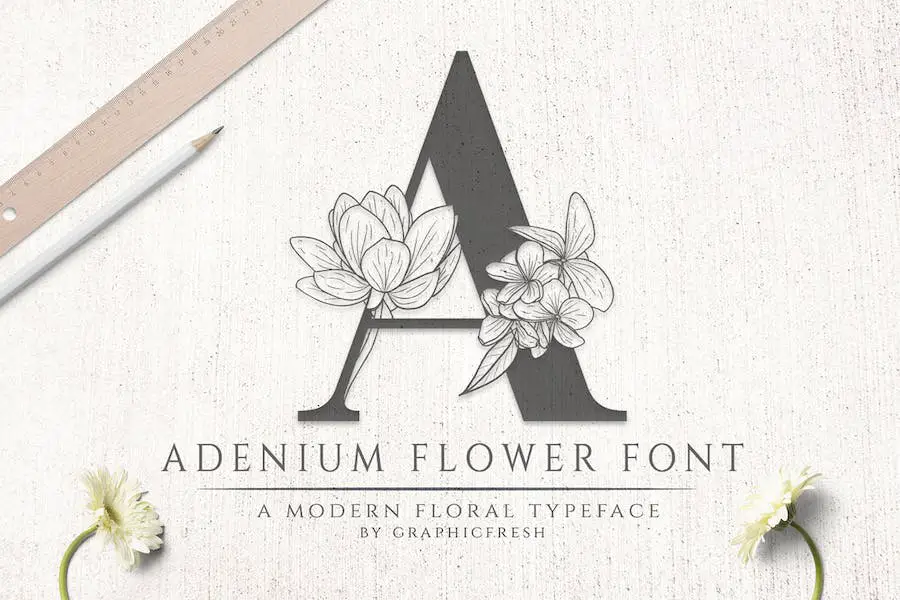
エレガントなフランジパニの花からインスピレーションを得た Adenium フォントは、プロジェクトに美しさをもたらします。 そのセリフ スタイルは、これらの見事な花の本質を完璧に捉えています。
ジャングルをテーマにした結婚式、海とクルーズスタイルのイベント、またはレストラン、ホテル、ビーチ リゾートのロゴを作成する場合でも、このフォントは理想的です。
Adenium を使用すると、ユニークなブランド アイデンティティ、スタイリッシュで優雅なロゴタイプ、または絶妙な結婚式の招待状をわずか数分で作成できます。
このフォントには各文字の 2 つのバージョンが用意されており、デザインに多用途性と多様性を加えます。 大文字と小文字のバージョンでは、創造性を発揮するための異なるオプションが提供されます。
アロア
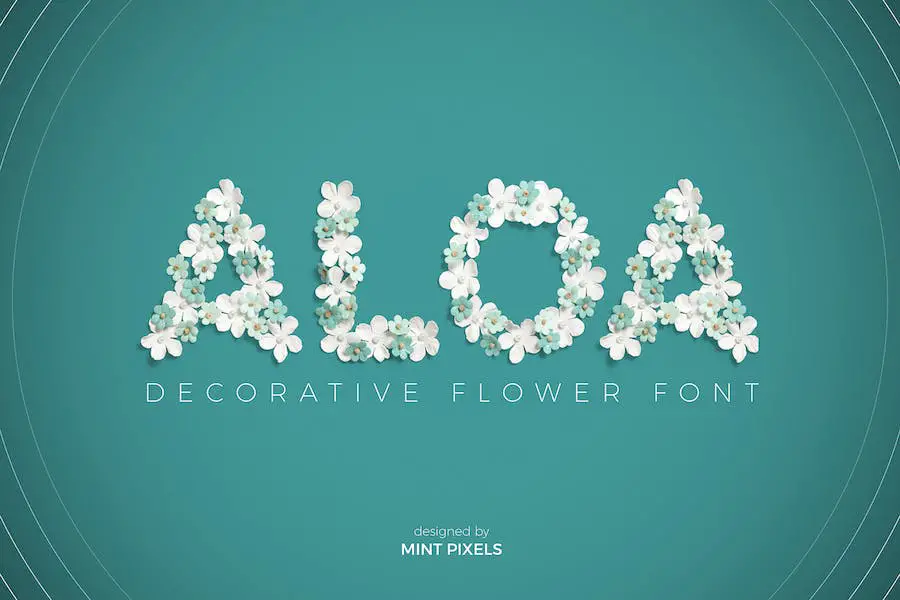
Aloa を使用すると、すべての文字、数字、句読点が得られるため、さまざまなデザイン プロジェクトに多用途なフォントになります。 結婚式の招待状、製品デザイン、イラスト、装飾品、工芸品などを作成する場合、このフォントは完璧な選択肢です。
ヴィグネリャ
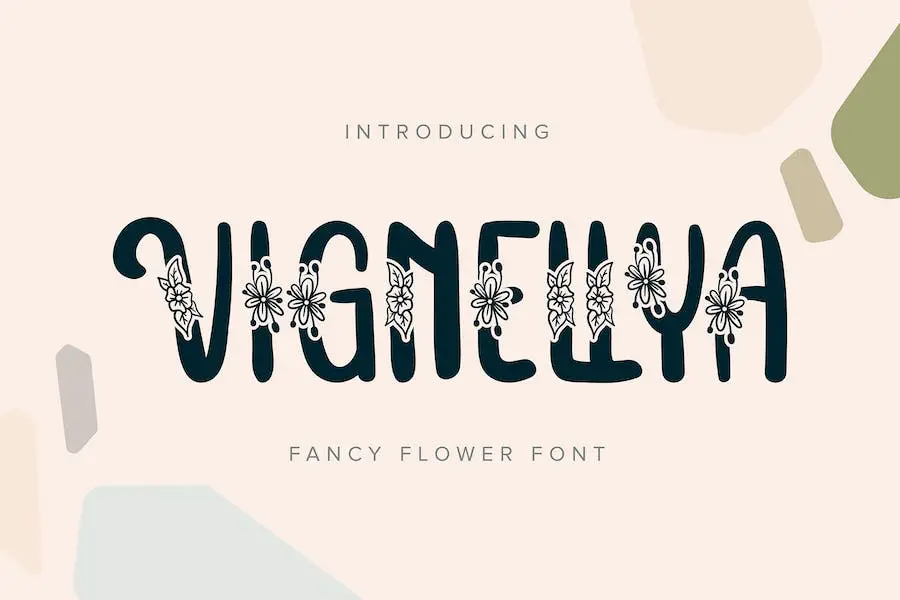
Vignellya は、美しいカリグラフィー スタイルの派手な花のフォントです。 素晴らしいグリーティング カード、ブランド資料、名刺、引用符、ポスターの作成など、プロジェクトを強化するのに最適です。
フォントには大量の代替文字が含まれており、文体セット、文体代替文字、コンテキスト代替文字、SWASH、合字などのさまざまなオープン タイプ機能に分かれています。
花の手描き
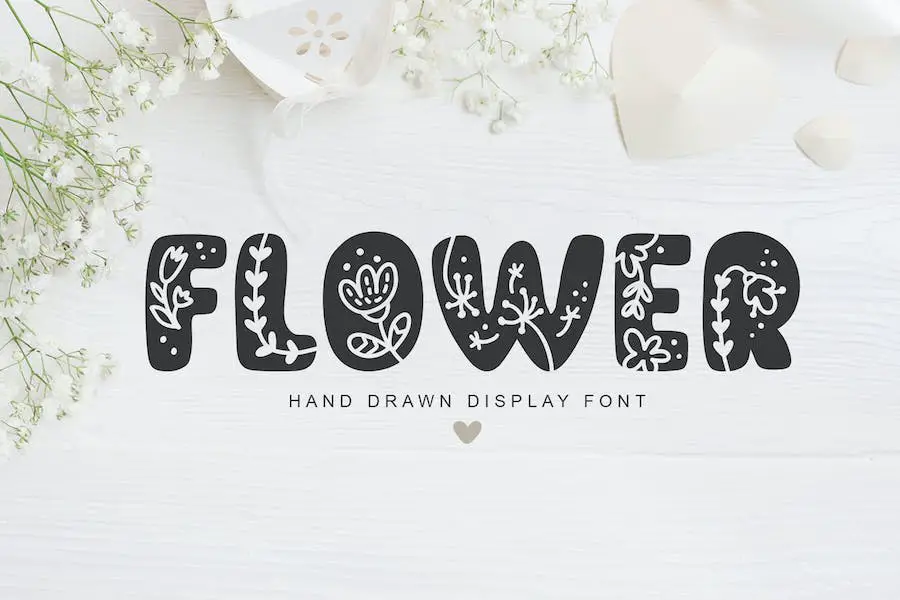
Flower Hand Drawn は、プロジェクトにスカンジナビアの魅力をもたらす楽しいバレンタイン フォントです。 手描きのスタイルと複雑なディテールを備えたこのフォントは、デザインにロマンチックで奇抜なタッチを加えるのに最適です。
このフォントにはさまざまなユニークな文字が含まれており、すべてが華やかなモノラインのハート、春の花、渦巻きで飾られています。 これらの楽しいデザイン要素により、Fflower Hand Drawn は結婚式やバレンタインデーのグリーティング カード、ロゴ、招待状などの作成に最適です。
ひまわり
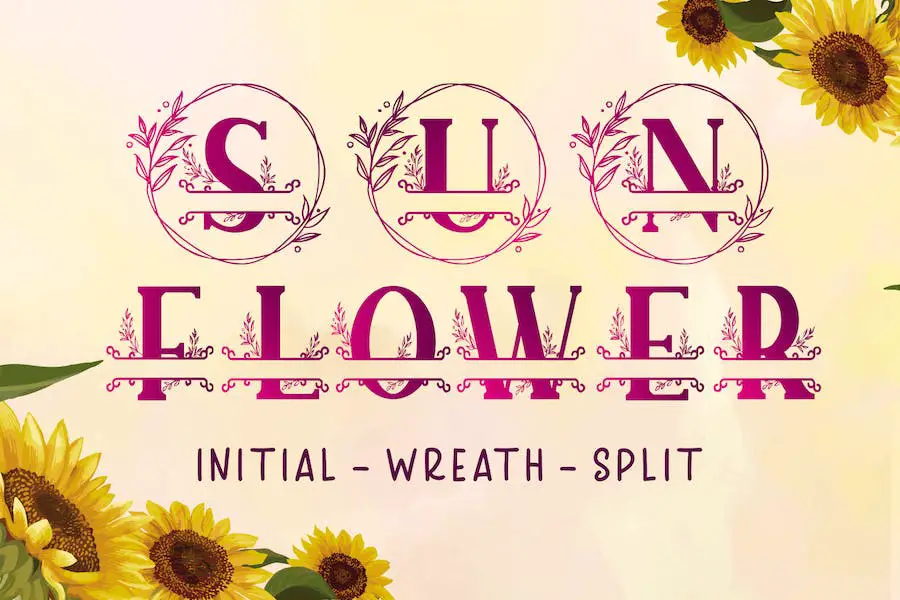
Sunflower は、あらゆるクラフト プロジェクトに個性的なタッチを加えるのに最適なフォントです。 PUA でエンコードされているため、すべてのグリフと合字に簡単にアクセスできます。 ブランド化プロジェクトに取り組んでいる場合でも、家の装飾に取り組んでいる場合でも、Sunflower は理想的なフォントです。
特に結婚式の招待状やブログのデザインに最適です。 ロゴや美しいフレームの作成にも使用できます。 Sunflower は多用途なので、ビジネス目的、ブックカバー、文具、マーケティング資料、雑誌などに使用できます。
キュートでスイートなモノグラム スタイルは、一緒に使用しても、別々に使用しても、あなたの工芸品にシックで陽気なタッチをもたらします。 ひまわりと恋に落ちて、素晴らしいデザインを作りましょう!
カンドレーヴァ
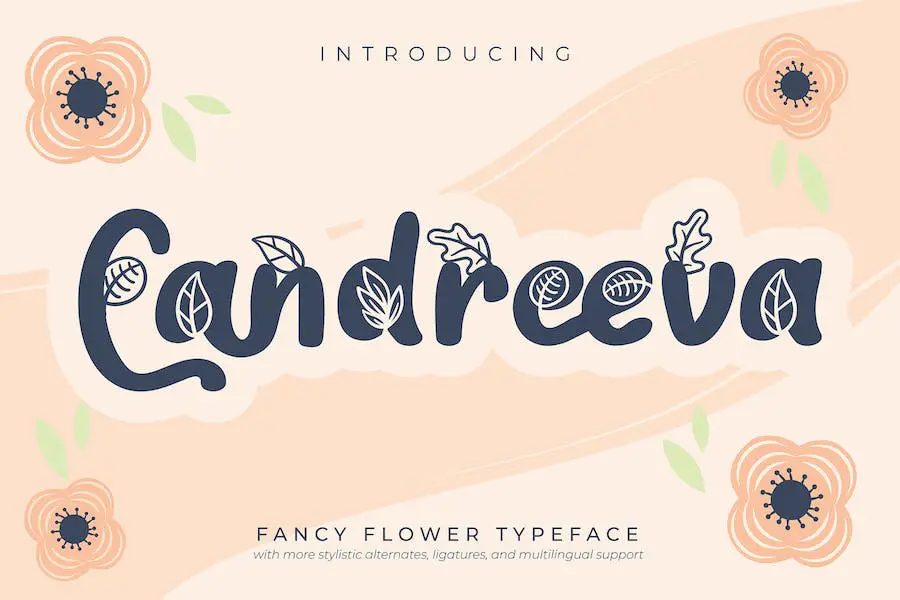
Candreeva は、あらゆるデザイン プロジェクトに優雅さを加える、派手な花の書体フォントです。 カリグラフィー スタイルと美しい曲線により、招待状、グリーティング カード、ブランド資料、名刺、引用符、ポスターなどに最適です。
このフォントには、文体セット、文体代替、コンテキスト代替、SWASH、合字など、いくつかの OpenType 機能に分割された代替文字が付属しています。
レイシャ
Reysha は、あらゆるデザイン プロジェクトに優雅さをもたらす、素晴らしいフラワー スクリプト フォントです。 カリグラフィー スタイルにより、招待状、グリーティング カード、ブランド資料、名刺、引用符、ポスターなどに美しく芸術的な外観を加えます。
このフォントには、スタイル セット、スタイル代替、コンテキスト代替、SWASH、合字などの代替文字の配列が付属しています。 これらの機能を使用すると、デザインをカスタマイズしてパーソナライズし、ユニークで個性的な雰囲気を加えることができます。
バホール
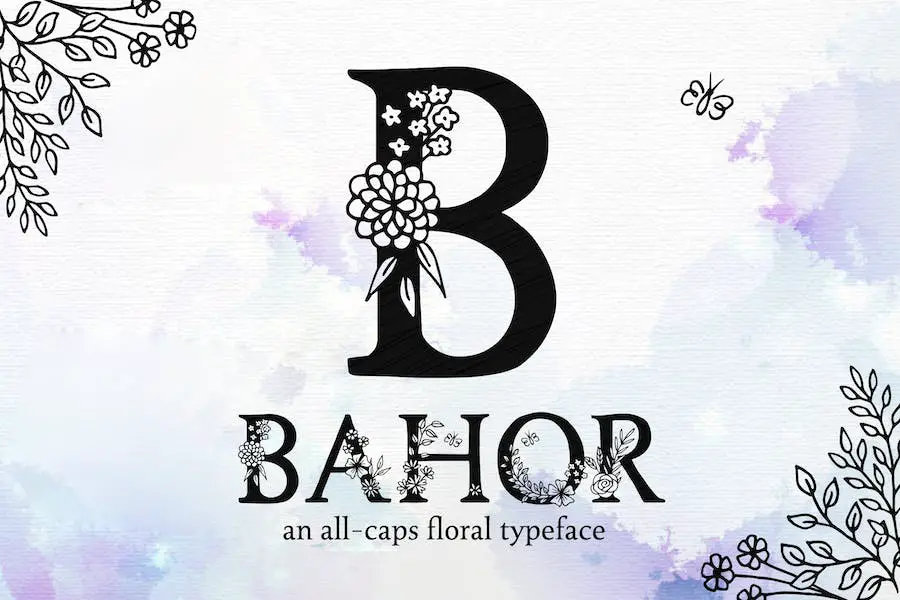
Bahor は、美しい花と絡み合ったエレガントな黒インクのセリフ文字を特徴とする、ユニークな手描きの花柄表示フォントです。 このフォントは、あらゆるプロジェクトに創造性と自然の美しさを加えます。
大文字と小文字で異なる複雑な花の装飾を備えた Bahor は、あなたの言葉を多様性とスタイルで際立たせます。
さらに、Bahor は多言語サポートを提供しているため、西ヨーロッパ、中央ヨーロッパ、東ヨーロッパの言語を扱うデザイナーにとって優れた選択肢となっています。
開花期
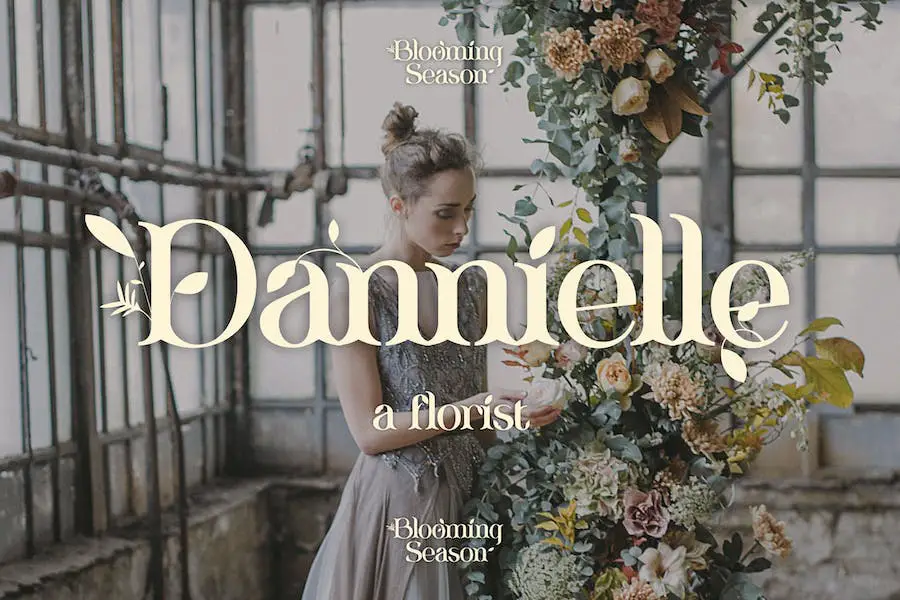
Blooming Season は、あらゆるクリエイティブなプロジェクトを強化する華やかなセリフ表示フォントです。 リガチャーとエレメントの機能により、デザインに見事でユニークな外観を提供するために慎重に作られています。
ロゴ、タイトル、結婚式の招待状、ポスターなどを制作している場合、このフォントはあなたの作品を次のレベルに引き上げます。 大文字のアウトライン バージョンも提供されており、カスタマイズのオプションがさらに増えています。
アフリカーンス語、アルバニア語、バハサ語、カタロニア語、デンマーク語、オランダ語、英語、エストニア語、フィンランド語、フランス語、ドイツ語、アイスランド語、イタリア語、ノルウェー語、ポルトガル語、スペイン語、スウェーデン語、ズールー語の言語がサポートされているこのフォントは多用途で、次の用途に使用できます。さまざまな言語でのプロジェクト。
Blooming Season を使用して、デザインに優雅さと洗練のタッチを与えます。
カロライナ
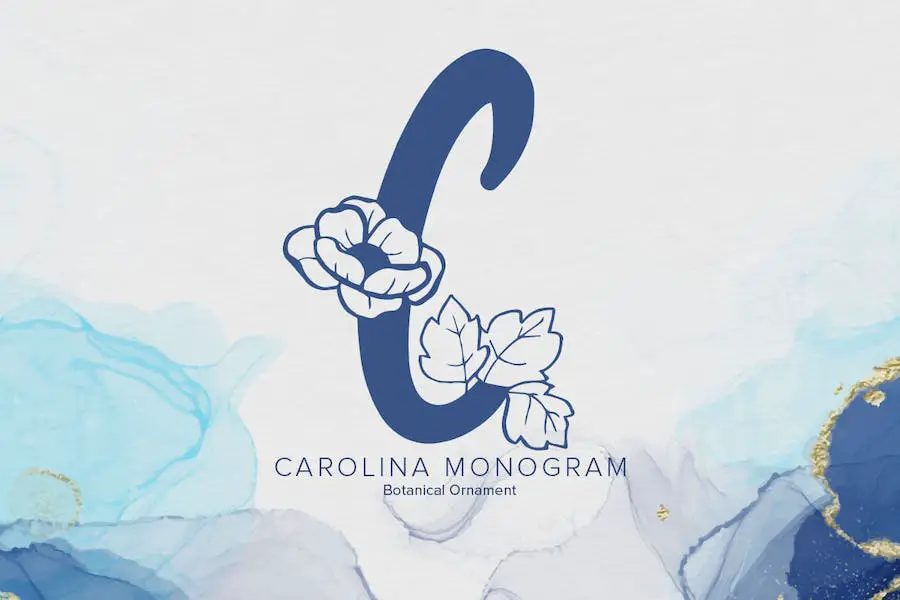
Carolina は、美しい花の要素を表現した「It Monogram」と呼ばれる素晴らしいフォントです。 このフォントをデザイン プロジェクトに組み込むと、それが創造的なアイデアにどのように命を吹き込むかがすぐにわかります。
独特で装飾的なスタイルを持つ Carolina は、デザインを向上させ、聴衆を魅了するのに最適です。
カロライナの花柄のアクセントがこのフォントを際立たせています。 各キャラクターは美しい花で繊細に飾られており、タイポグラフィーに魅惑的なタッチを加えます。
レモングローリー
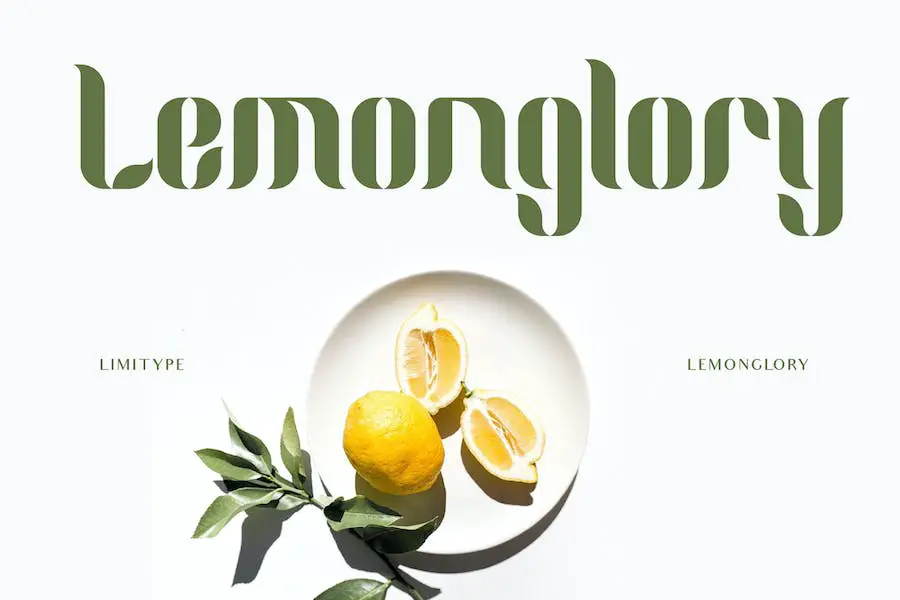
Lemonglory は、エレガントな葉の形からインスピレーションを得たモダンなフォントです。 ディスプレイ、ロゴ、見出し、ポスターなど、デザインに有機的なタッチを加えるのに最適です。
このフォントのユニークな形状は必ず目を引き、プロジェクトに新鮮で現代的な雰囲気を与えます。 Lemonglory で自己主張をする準備をしましょう!
庭
Garden は、Salt & Pepper Designs の「It Flower」と呼ばれる新しいフォントで、グラフィック デザイン プロジェクトを向上させます。
この太くて素晴らしいフォントは、目を引くヘッダーの作成に最適であり、大きなテキスト ブロックにも使用できます。 大文字と小文字を組み合わせて代替文字を作成すると、無限の可能性を探索して楽しむことができます。